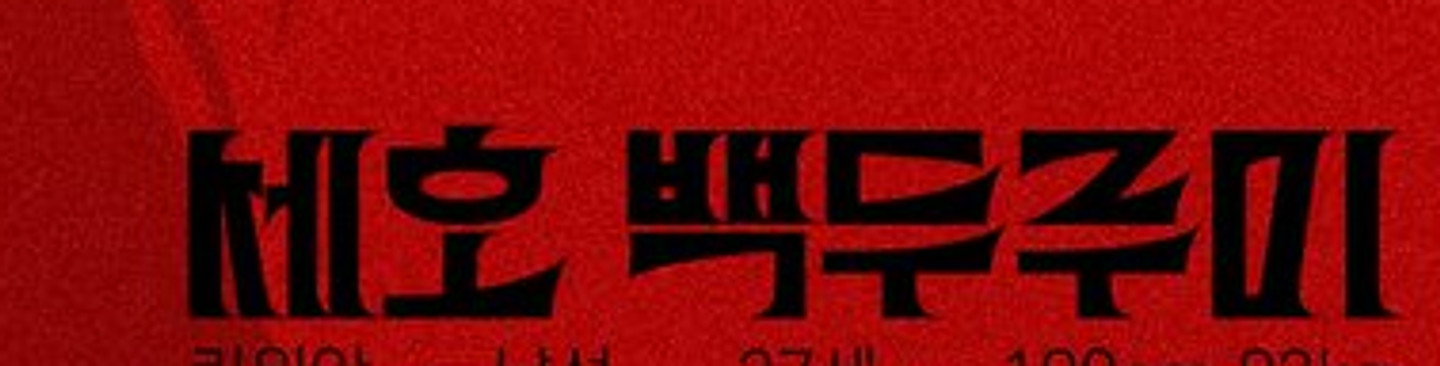
뭘까요?? 혹시 영어 폰트도 아시면 같이 알려주시면 감사하겠습니다!!!
영문이랑 국문 폰트 뭘까요
폰트명 알고 계신분?~~~~부탁드립니다.
굴림체? 느낌인데 무슨 폰트인지 궁금합니다 ㅠㅠ
이거뭘까요ㅠㅠㅠㅠㅠㅠ꼭찾고싶어요 / 열심히 서치해서 찾았어요!!! 그린버터 어린시절 볼드 입니댜